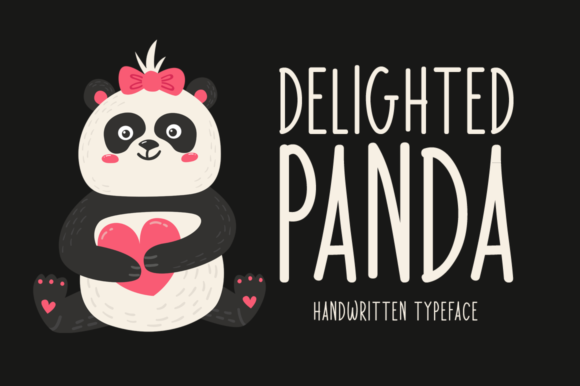
Creativefabrica Delighted Panda Font
[Creativefabrica] Delighted Panda Font
Delighted Panda - это милый и простой рукописный шрифт.
Его естественный и уникальный стиль делает его невероятно подходящим для большого количества дизайнов.